Omaggio alla tipografia. Un ristorante tra arte grafica, culinaria ed architettonica
Il ristorante Alla lettera progettato da Yet|Matilde, Francesco Stassi e Nicola Di Fonso, è un omaggio ironico allatipografia, alla forma e al significato delle parole. Non a caso si affaccia su una location eccezionale, Piazza Bodoni, tra le più belle e ariose del capoluogo piemontese. Questa, infatti, porta il nome del creatore dell’omonimo font serif, riconoscibile per il forte contrasto tra le linee spesse e quelle sottili. Ed è proprio il carattere Bodoni ad essere il filo conduttore dell’interior design, un mix sapiente di grafica, riciclo creativoe oggetti industriali personalizzati.
La lettera “O” è riproposta in diverse dimensioni e famiglie di font su pareti e accessori, diventando il logotipo del ristorante.Rappresenta la forma della pizza, piatto forte del locale, sempre simile ma mai uguale, perché fatta a mano e, ogni volta, personalizzata.
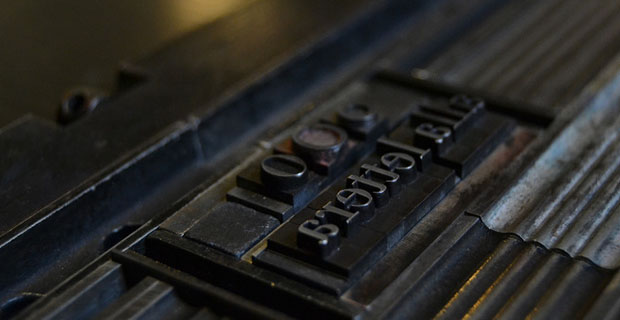
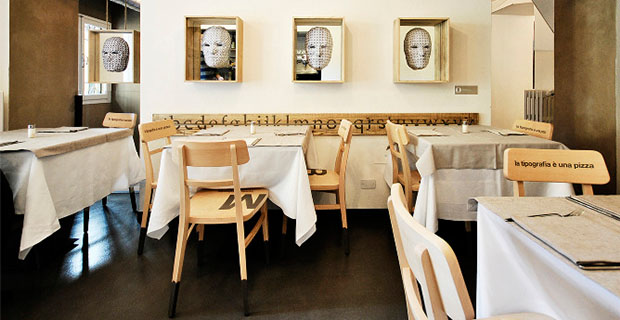
La pizzeria editoriale ricorda, inoltre, il parallelismo tra ingrediente e carattere tipografico: entrambi ripetuti creano risultati sempre nuovi e creativi.
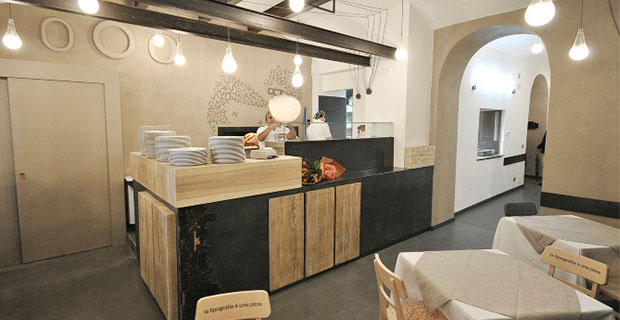
PAROLE, PAROLE…
Marrone, beige, crema e panna sono i colori predominanti del ristorante: su questo scenario si sviluppa il dialogo tra arte grafica, culinaria e architettonica. All’ingresso, il bancone bar e di preparazione delle pizze è caratterizzato da linee pulite, materiali nobili quali legno e ferro; di sfondo la profonda e rettangolare bocca del forno sembra borbottare parole poi impresse sulla parete.
Si allarga il locale dedicando tutto lo spazio a tavoli quadrati e alle tipiche sedie in legno, marchiate sugli schienali e sedute da brevi motti e lettering a grande dimensione .
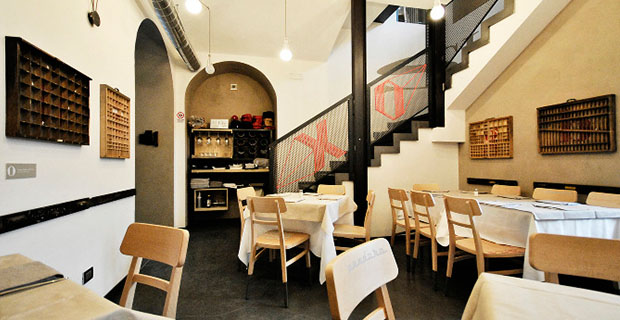
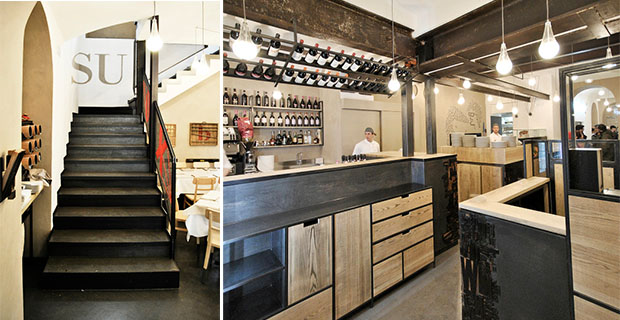
Sulle porte e pareti sono ripetute le tipiche destinazioni d’uso dei locali commerciali (toilette, zona cucina…), aggiungendo alla semplice informazione un valore didattico oltre che decorativo. “Un buon pranzo giova molto alla conversazione” recita una parete, mentre parole isolate sono tradotte in varie lingue.
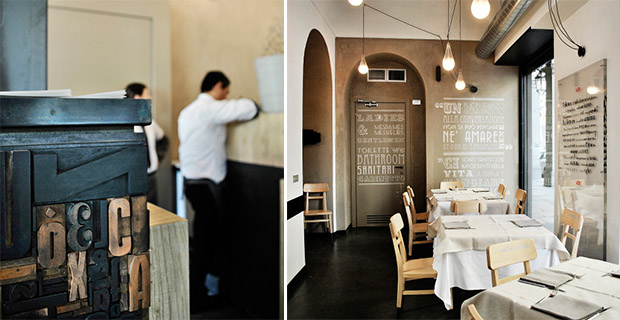
Il menù è quotidiano e la sua grafica è quella tipica dei vecchi giornali stampati. Anche l’allestimento del locale varia e “si muove” in analogia con l’antico mestiere dei tipografi che utilizzavano appunto caratteri mobili, componibili e riciclabili. I camerieri indossano divise firmate da Antonio Rizza con tanto di copri–maniche, ed infine, i tovaglioli scuri presentano un’asola per agganciarli al bottone della camicia.
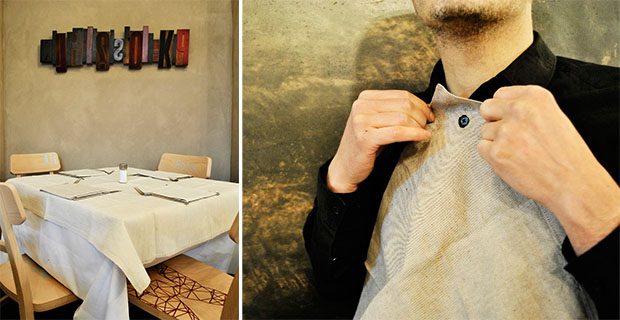
“Specchio servo delle mie brame chi è la più bella del reame?” Il testo posto sulla parete scura del bagno, diventa comprensibile grazie al suo riflesso sullo specchio adiacente. In cucina il neon “Che fame” allevia l’attesa del cliente, che può anche intravedere dalla fessura come i cuochi preparino le pietanze in cucina. L’appendiabiti è realizzato da semplici corde su cui sono ancorati traduzioni di “buono” in varie lingue, mentre su alcune pareti appaiono i bellissimi casellari di legno, in cui una volta erano riposti i bianchi e altri strumenti tipografici.
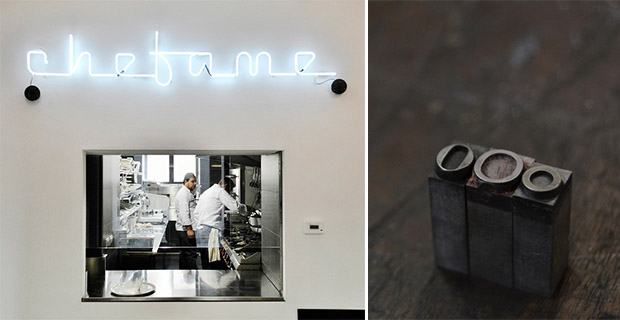
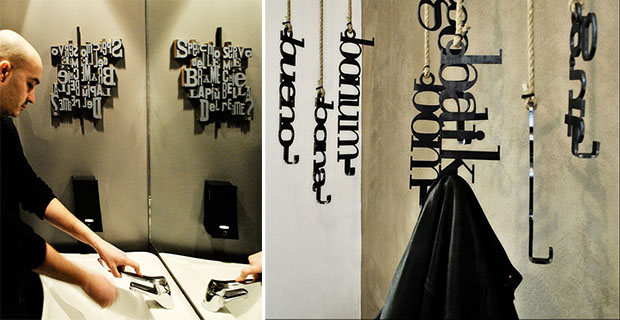
Gli ambienti, tutti progettati da eccellenti grafici e designer, sono originali e ricercati: le travi scure d’acciaio rimangono a vista sui soffitti chiari, mentre una fitta rete di lampade a bulbo scende in maniera irregolare sui tavoli.
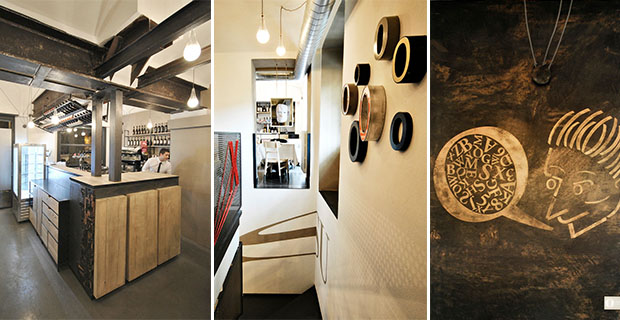
Tanta ricercatezza non comporta un effetto finale artificioso e “perfettino”, perché tutti gli allestimenti sono work–in progress: periodicamente il locale accoglie opere di giovani artisti ed è sempre alla ricerca di nuove sperimentazioni.